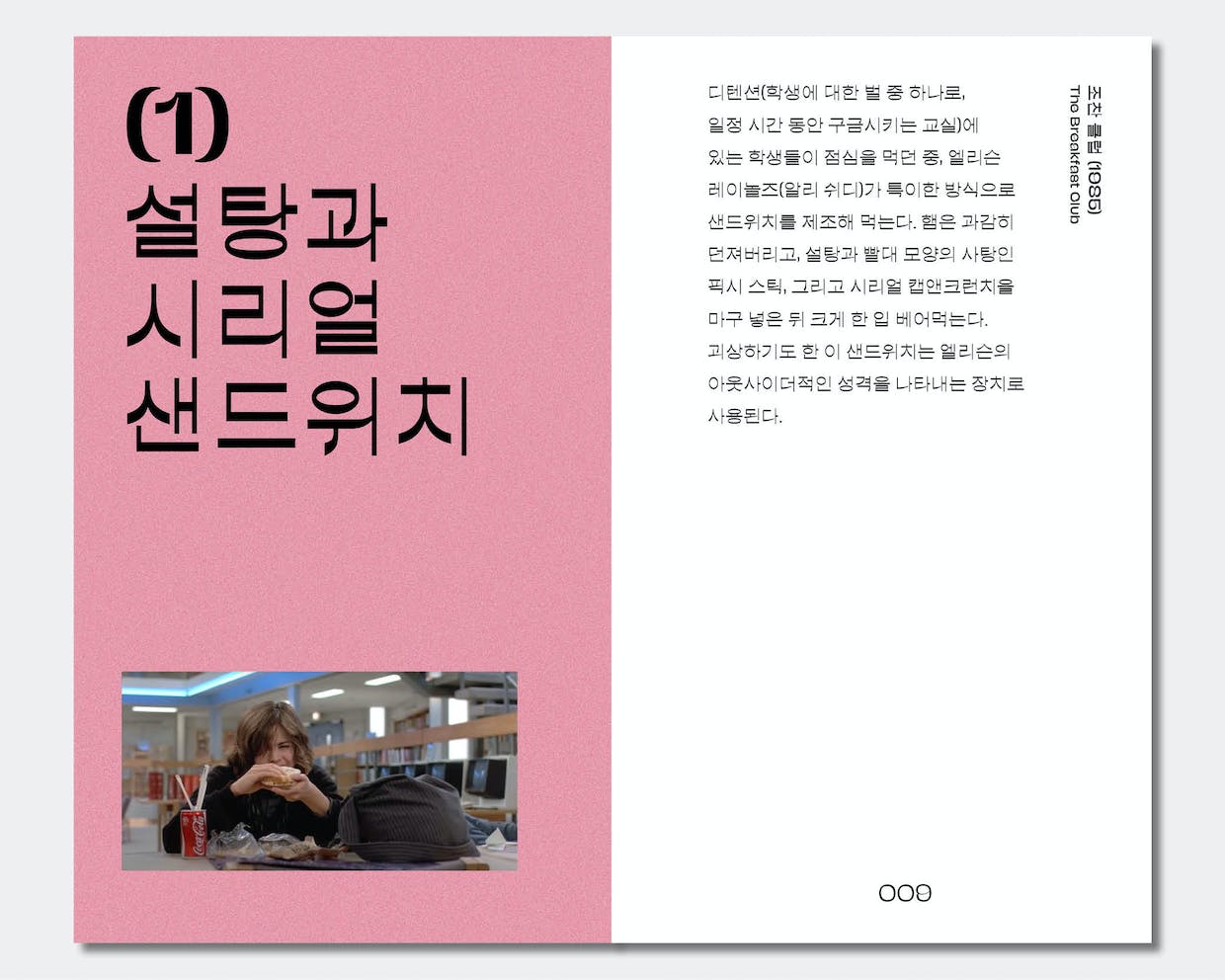
이 폰트 뭔지 알려주세요! siy*** 2023.03.05 ‘설탕과 시리얼 샌드위치’ 부분 폰트가 무엇인지 궁금합니다 댓글 0 등록 sta*** 태-공작 같네요 https://thefont.kr/shop/item.php?it_id=A1011&ca_id=5030&page=1 Rix슬릭도 좀 비슷하네요. '위' 자의 'ㅜ' 모양이 좀 다르긴 하지만 https://www.rixfontcloud.com/Font/Detail/RixSleek 2023-03-06 답글 달기 댓글 더보기 쉽고 빠르게 가장 비슷한 폰트를 알고 싶다면? 이미지로 검색하기
태-공작 같네요 https://thefont.kr/shop/item.php?it_id=A1011&ca_id=5030&page=1 Rix슬릭도 좀 비슷하네요. '위' 자의 'ㅜ' 모양이 좀 다르긴 하지만 https://www.rixfontcloud.com/Font/Detail/RixSleek